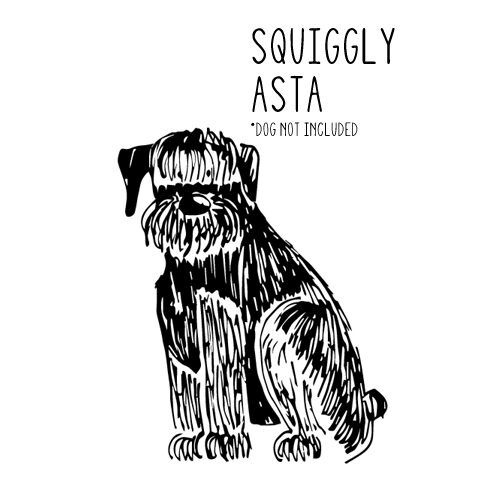
Squiggly Asta präsentiert sich als verspielte und zugleich elegante handschriftliche Schriftart, die von der talentierten Ana Parracho entworfen wurde. Mit ihrem leichten Strich und dem extrem schmalen Laufbild verleiht dieser Font jedem Designprojekt eine einzigartige Mischung aus Charme und Raffinesse. Die kunstvollen Unregelmäßigkeiten von Squiggly Asta ahmen die liebenswerten Imperfektionen natürlicher Handschrift nach und verleihen der digitalen Kommunikation eine persönliche Note.
Dieser Stil strahlt eine nahbare Atmosphäre aus, die perfekt für Einladungen, Brandings und Werbekampagnen geeignet ist, die eine handgemachte Anmutung erfordern, ohne dabei an Lesbarkeit einzubüßen. Die markanten Schnörkel und Kurven eignen sich hervorragend für kreative Vorhaben, die eine Schriftart mit Charakter und Persönlichkeit verlangen. Ob Sie Grafiken für soziale Medien erstellen oder Briefpapier gestalten – Squiggly Asta bietet Vielseitigkeit in einem ästhetisch ansprechenden Gesamtpaket, das jeden Betrachter in seinen Bann zieht.
Squiggly Asta ist eine handgezeichnete All-Caps-Schrift mit 227 Glyphen, darunter:
>> A-Z | 0-9
>> Satzzeichen
>> Akzente.